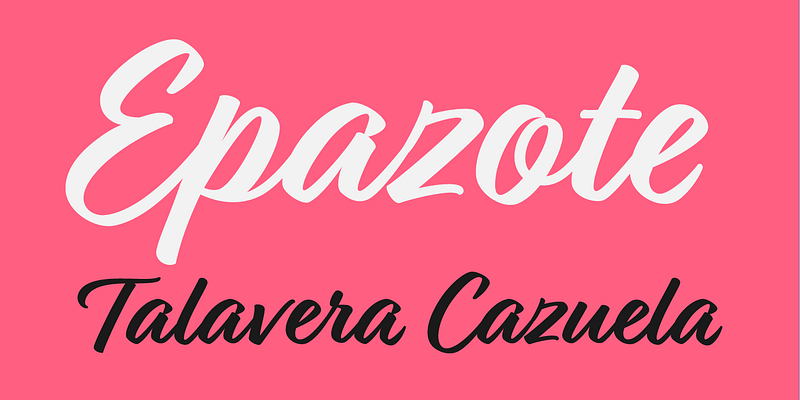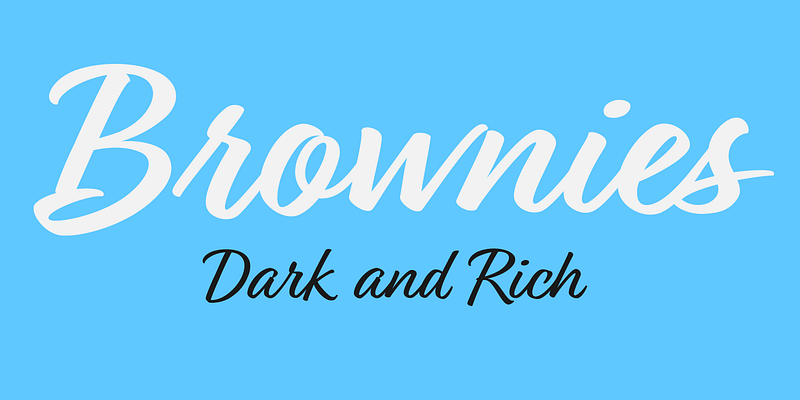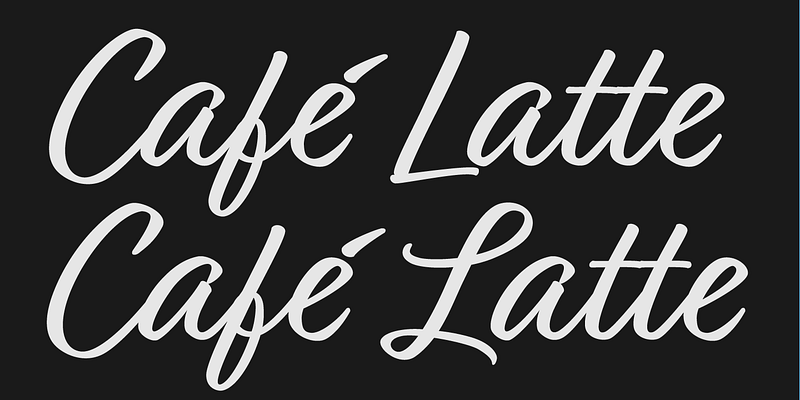
Relation est une belle police d’écriture au pinceau au look original et moderne du lettrage à la main. Sa variante (Relation Two) possède un style de majuscules différent. Chaque version est disponible en deux graisses : Regular et Bold. Pour tirer le meilleur parti de cette police, assurez-vous d’utiliser un programme qui a des capacités OpenType.
Jess Latham a commencé à concevoir des polices de caractères en 1997. Sa fonderie se concentre principalement sur les caractères de titrage et les ornements. Bon nombre de ses typographies commerciales se sont hissées parmi les produits les plus vendus sur le site myfonts.com. Vous avez probablement vu son travail dans les allées de votre épicerie, sur des couvertures de livres, des magazines, à la télé et dans beaucoup d’autres endroits.